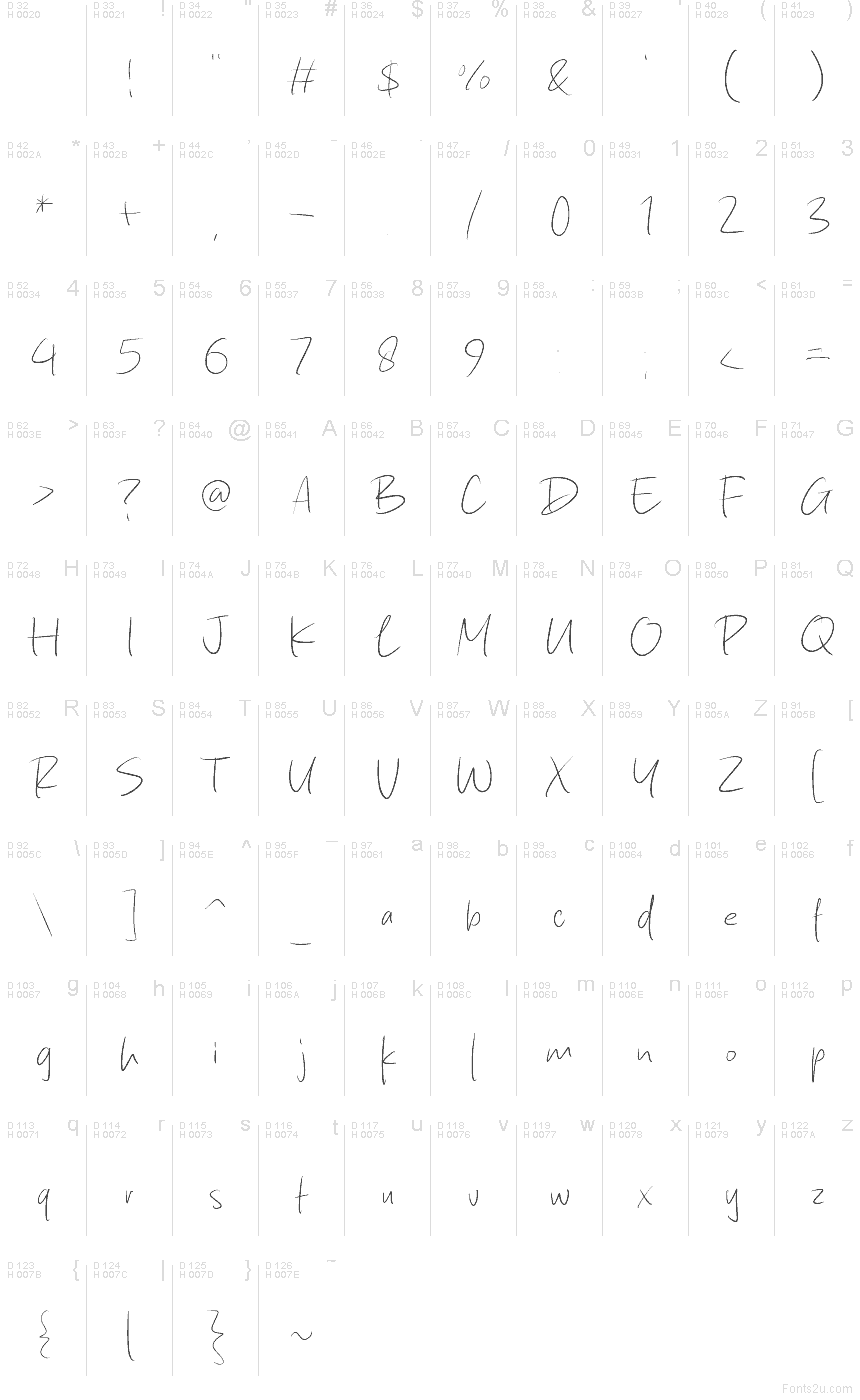
Majestic Face
Majestic Face, di Origin Type, è un carattere gratuito in stile firma autografa, leggero e arioso. Le lettere si distinguono per i tratti lunghi e sinuosi e un movimento ampio ed elegante, che le conferisce il ritmo disinvolto di una firma personale, allontanandosi dall'aspetto rigido di un classico script a pennello.
È perfetto ovunque tu voglia aggiungere un tocco personale e alla moda: branding di boutique, packaging di cosmetici, carta intestata per matrimoni, header per i social media o titoli di riviste. Essendo un font gratuito, è ideale anche per loghi, cartelli con titoli e brevi citazioni, poiché le sue asole alte e le connessioni fluenti conferiscono anche a poche parole una presenza graziosa e scritta a mano.